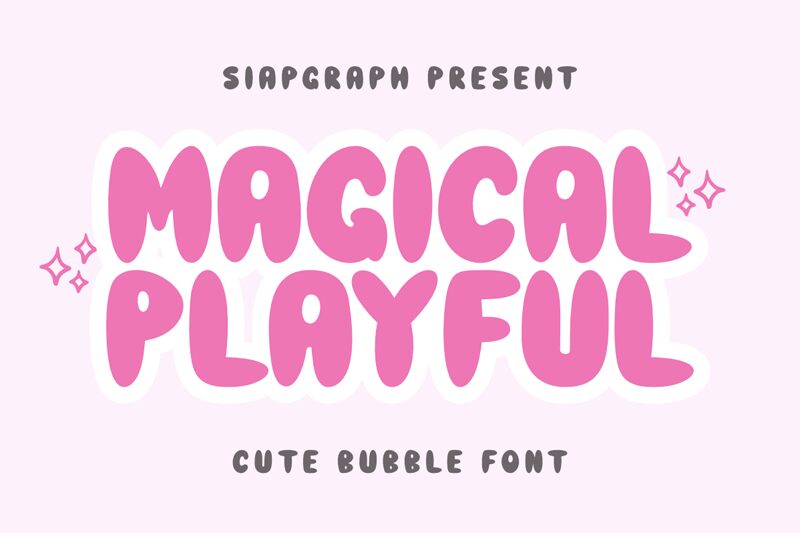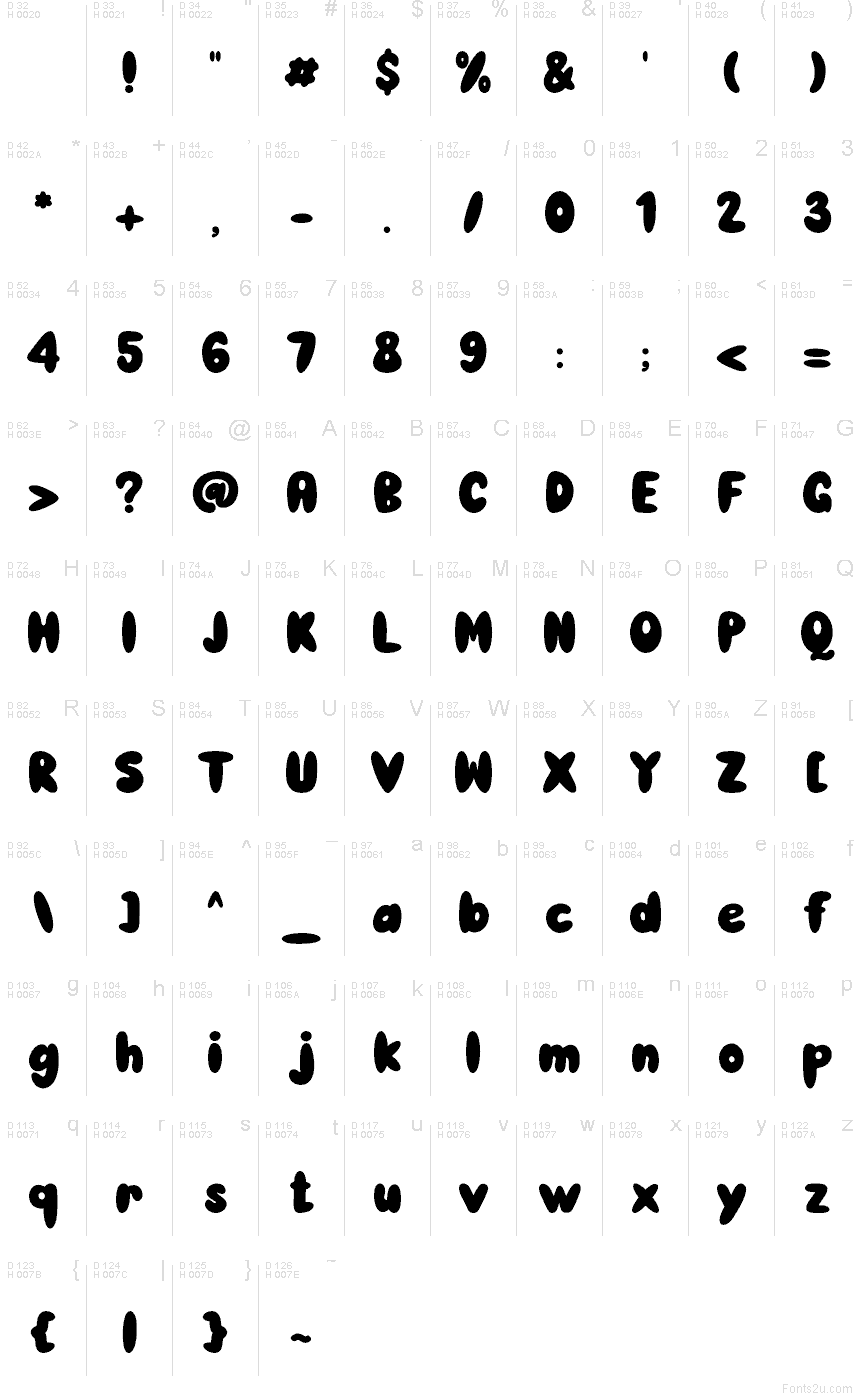
Magical Playful Regular
Magical Playful от SiapGraph - это бесплатный акцидентный шрифт в мультяшном стиле. Он состоит из мягких, «надутых» букв с живым и динамичным ритмом. Округлые формы придают дизайну забавный, детский характер, который остается неизменным во всем наборе.
Приглашения на день рождения, школьные плакаты, упаковки игрушек, обложки детских книг и оформление кондитерских - везде этот шрифт будет смотреться органично. Он идеально подходит для коротких заголовков и праздничных вывесок: благодаря объемным изгибам и легкой мультяшной энергии слова превращаются в яркий графический элемент, а не просто в обычный текст.